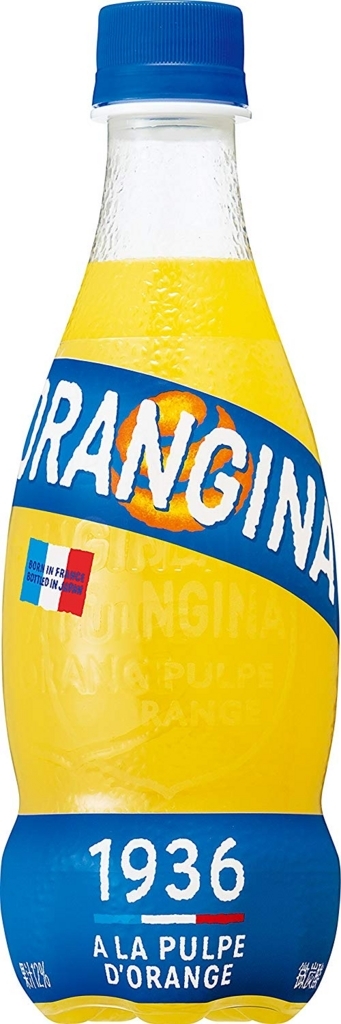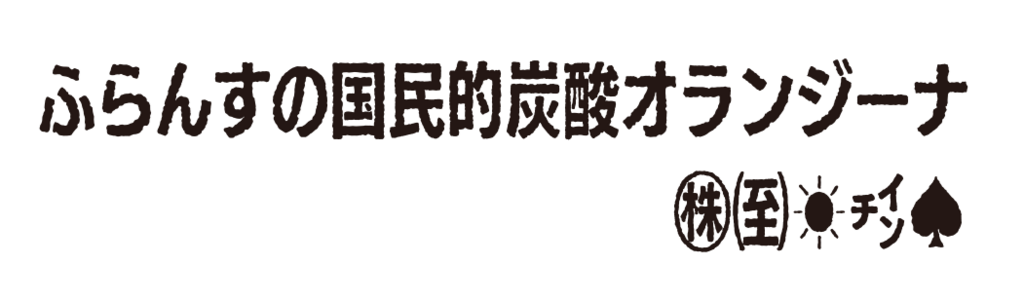
サントリー社製品「オランジーナ」専用フォント
フォントワークスがサントリーホールディングス株式会社が発売している飲料「オランジーナ」専用の和文フォントを制作したことを2018年8月11日に発表した。
また、オランジーナオリジナル書体である欧文部分のフォント化も行ったとのことだ。
和文フォントのベースにはフォントワークス「UD角ゴC70Pro-B」が採用し、オランジーナオリジナルデザインの欧文の特徴である文字のアウトラインをぼこぼこさせたようなデザインにあわせて、「UD角ゴC70Pro-B」を一律でぼこぼこさせる処理を施した。
さらに「かな」と頻出の漢字など特に使用頻度が高い文字について更に欧文書体のデザインとあうよう一字一字に特別な処理を施している。
オランジーナ専用フォントの使用箇所は、オランジーナ公式Webページなどに使われている。